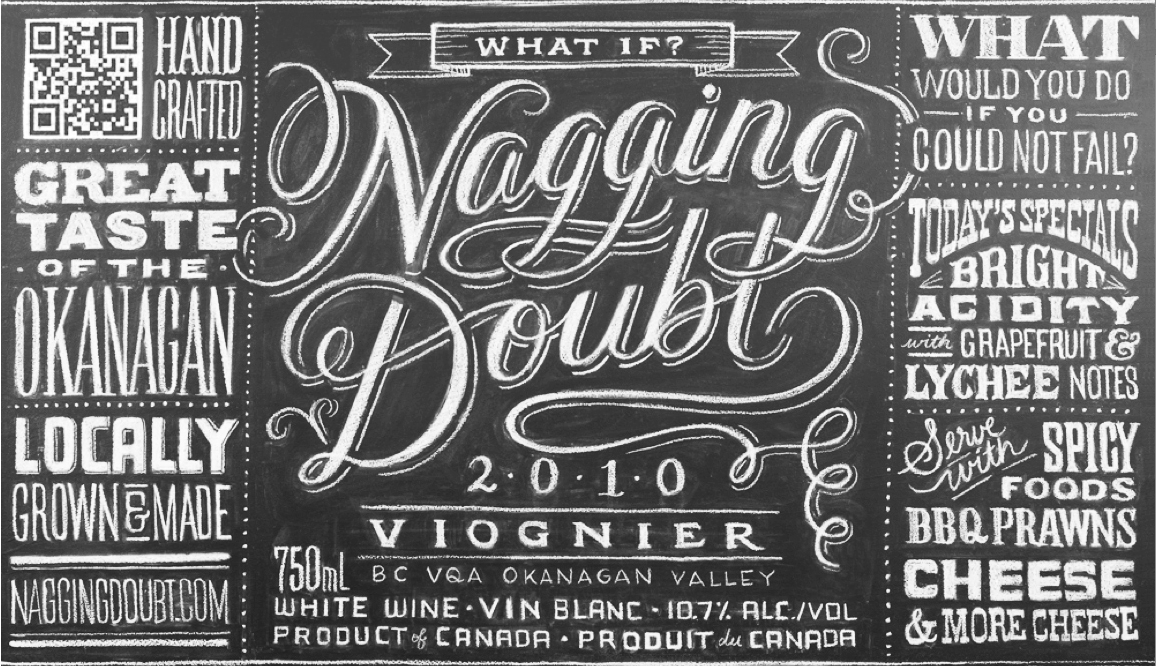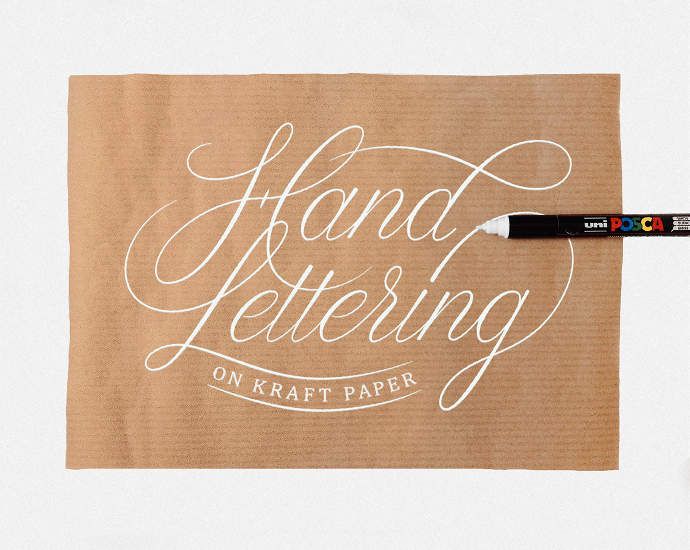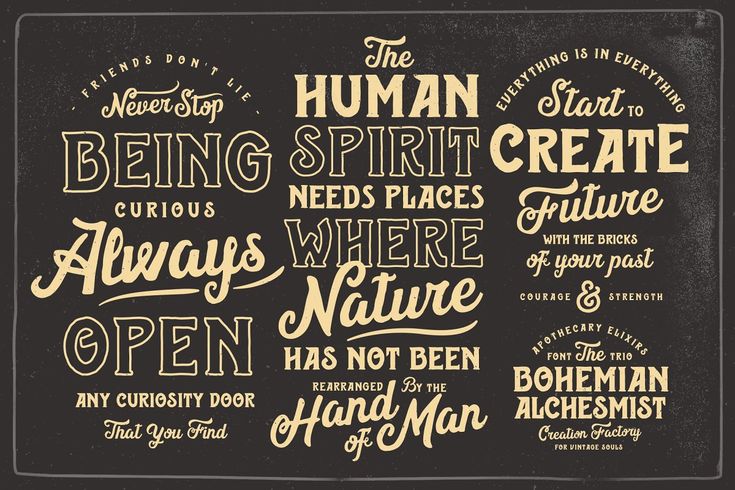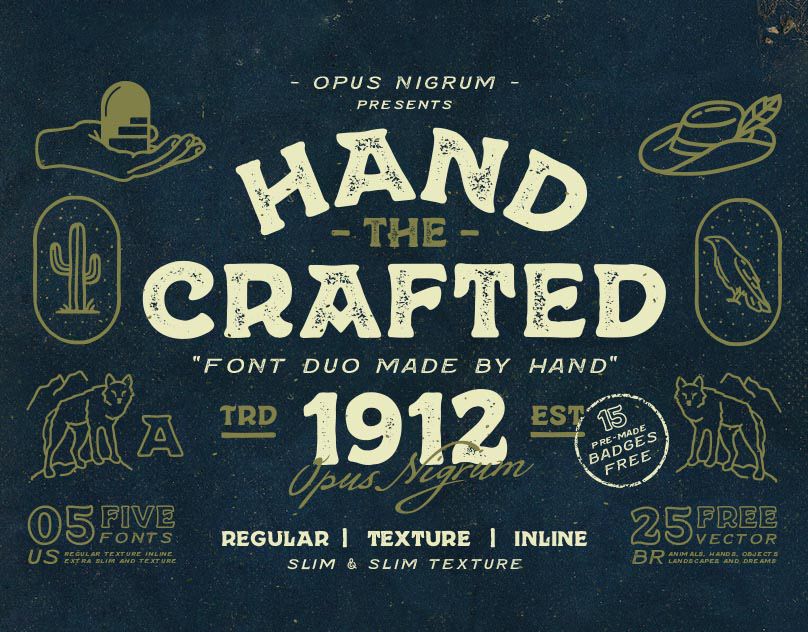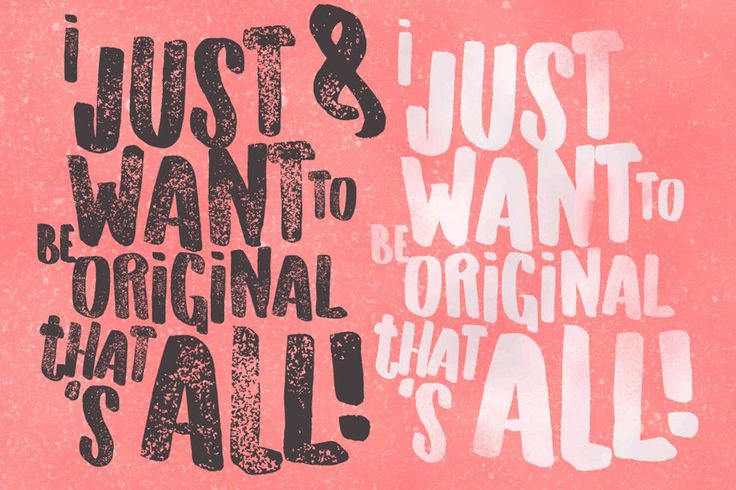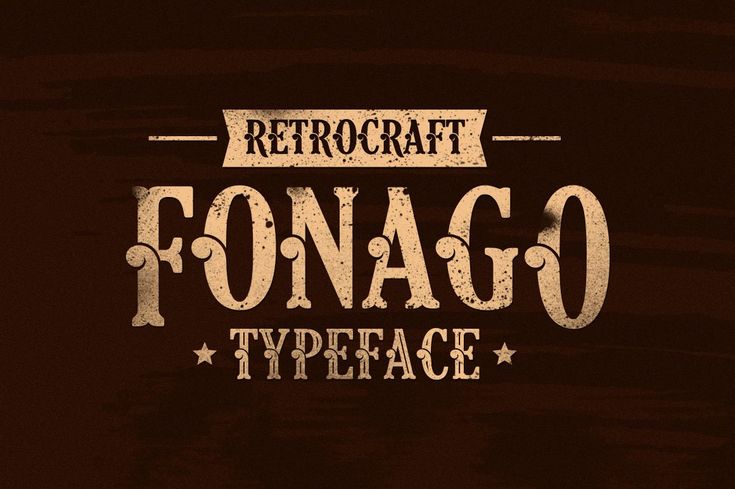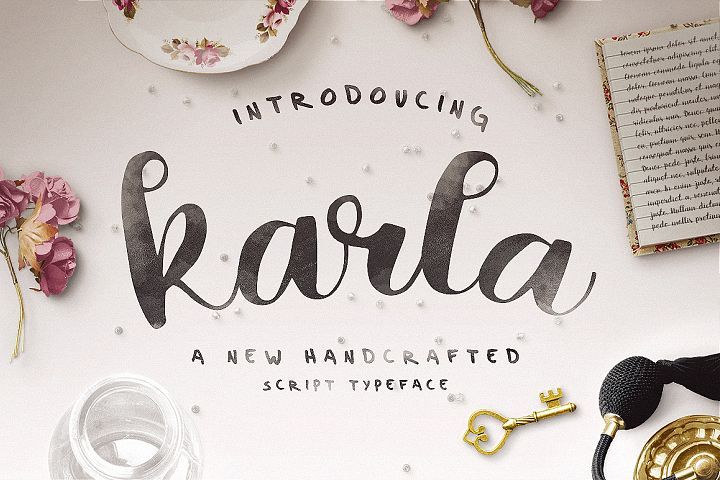
Крафтовые шрифты: 42+ лучших кириллических шрифта бесплатно (обновлено в 2021)
Что такое шрифты в кривых и шрифты в векторе
Для начала маленькое отступление:
Многие уже знают, что графика делится на два типа: векторная и растровая.
Растровое изображение, как мозаика, складывается из множества маленьких точек (пикселей).
Каждая точка содержит информацию о цвете. Если растровое изображение сильно увеличить – это множество маленьких квадратиков (пикселей) станет заметным, картинка сильно потеряет в качестве, так как между квадратиками есть расстояние.
Они не слиты в единое целое. При «растягивании» такая картинка словно
Векторное изображение состоит не из пикселей, а из множества опорных точек и соединяющих их кривых. Оно описывается математически и его можно увеличивать сколько угодно без потери качества.
Оно будет «растягиваться» под нужный вам размер, при этом вес самого файла меняться не будет, потому что математическое описание (грубо говоря, формула) тоже не будет меняться.
А вот теперь необходимо ввести еще одно понятие – векторные шрифты.
К шрифтам относится все то, что вы можете набрать на клавиатуре – буквы и символы.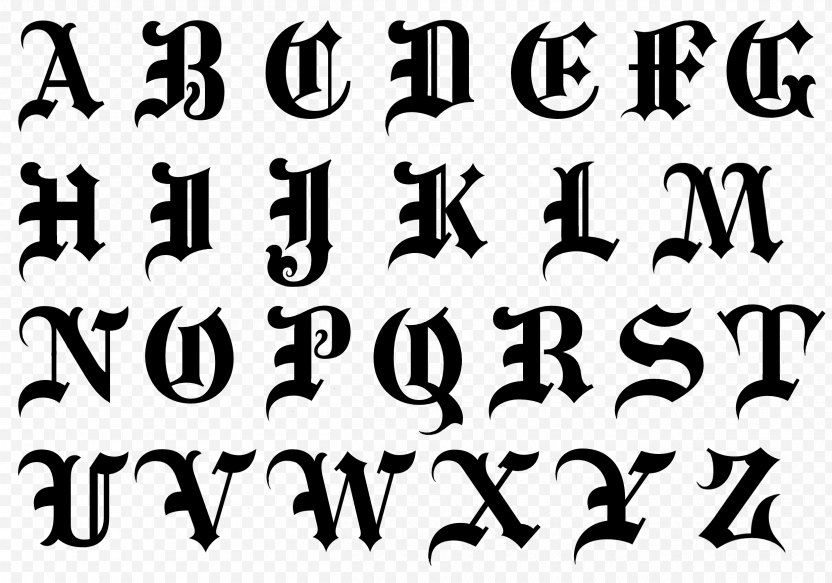
Все вы наверняка сталкивались с ситуациями, когда какой-то шрифт в программе поддерживает только кириллицу или латиницу, и вы не можете использовать его для двух языков. Это хороший пример отсутствия соответствующей формулы. В таком случае мы можем сказать – такого шрифта для кириллицы просто нет. И «нарисовать» его при помощи клавиш клавиатуры мы никак не сможем. То же самое, если вы хотите сделать шрифт жирнее (bold), а математическое описание такого шрифта отсутствует – такого шрифта просто нет.
Есть еще такое понятие, как растровый шрифт.
Просто говоря, это шрифт – картинка. Каждый знак которого предоставлен в виде рядов растровых точек (пикселей), последовательно заполняющих его контур. Изменить масштаб такого шрифта – большая проблема, поэтому сейчас растровые шрифты почти полностью заменены векторными.
Когда от заказчика требуют шрифты в векторе (в установочных файлах)?
НО! Как говорилось выше – у каждого шрифта есть определенное количество вариантов начертаний, и для каждого вида требуется свой отдельный файл установки.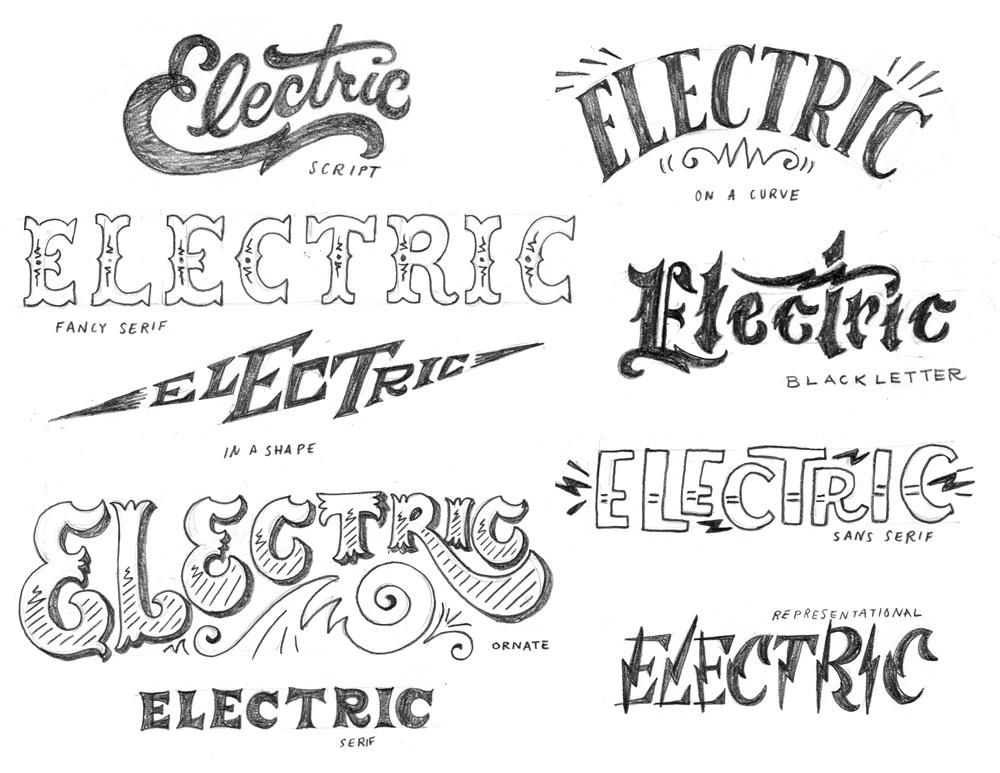
Поэтому, если вы просите сделать шрифт жирнее, а файла с таким описанием шрифта Вы не прислали или создатель шрифта не предусмотрел возможность именно для этого шрифта такого начертания (что часто встречается в декоративных шрифтах, имитирующий рукописный, чаще всего в названии присутствует script), мы не сможем сделать этого «экологичным» способом.
Нам придется искусственно обводить шрифт, что повлечет за собой потерю его оригинального начертания и скажется на эстетике макета (изменится расстояние между буквами, ухудшится читаемость шрифта и т.п.). Дизайн полиграфической продукции пострадает.
И еще: шрифты в векторе и шрифты «в кривых» — это не одно и то же.
Что такое шрифты в кривых и когда нужны они?
Шрифт в кривых – это только сами линии шрифта, т.е это уже не шрифт, а векторная картинка.
То есть изменить текст (исправить букву, дописать слова, изменить начертание) в таком макете при отсутствии у нас данного шрифта в виде установочного файла мы не сможем.
Это «замороженная» версия векторного шрифта, его «слепок».
Мы просим макет со шрифтами «в кривых» в том случае, если от нас не требуется менять текст. Текст уже есть в макете, но в макете надо сделать какие то изменения, не касающиеся текстовой части. Скажем, надо подвинуть, поменять текстовый блок местами с картинкой или просто добавить другие иллюстрации. Или же поменять формат изделия, поменять фон и т.п.
Мы также просим перевести шрифты «в кривые» в том случае, если видим, что шрифт «слетел» в pdf, или вы прислали макет не соответствующий требованиям (т.е. не печатаный pdf)
Как перевести шрифты в кривые?
Если перед сдачей ГОТОВОГО макета в печать шрифты в нем необходимо перевести в кривые, для этого необходимо выделить текст и нажать комбинации клавиш:
15. ШРИФТ BESOTTED MODERN CALLIGRAPHY
Нам очень нравится шрифт Besotted Modern Calligraphy Font , который является частью набора за ноябрь 2019 года .
И мы уверены, что вам понравится этот женственный рукописный шрифт для многих ваших дизайнов.